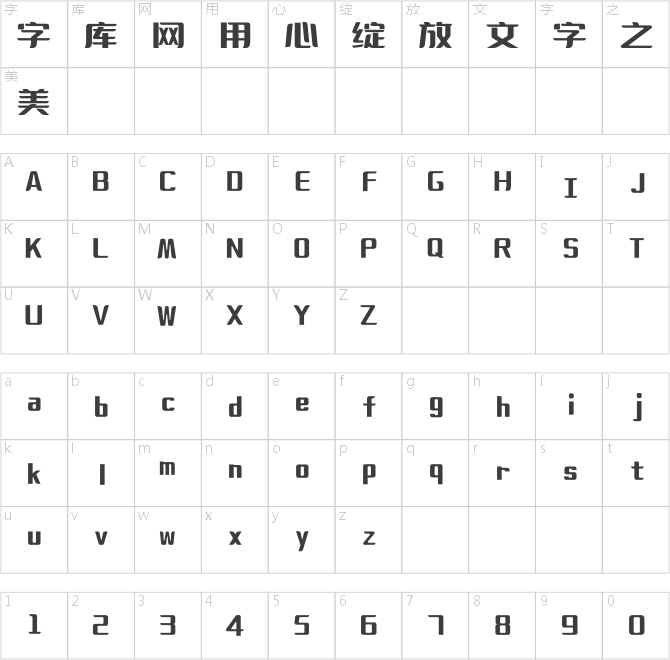
上首漠云體,字體筆畫圓潤,橫斜筆進行了倒圓,整體導圓處理。字庫整體簡約時尚,現代感十足,適用于搭配標志、廣告標語、商業廣告等高端屬性。
上首漠云體字體字庫是一款讓人賞心悅目、百看不厭的中文字體,適合各類廣告和產品包裝設計應用,字體大小2.6MB,格式為ttf字體,上傳用戶是上首造字,作者/版權方為上首造字